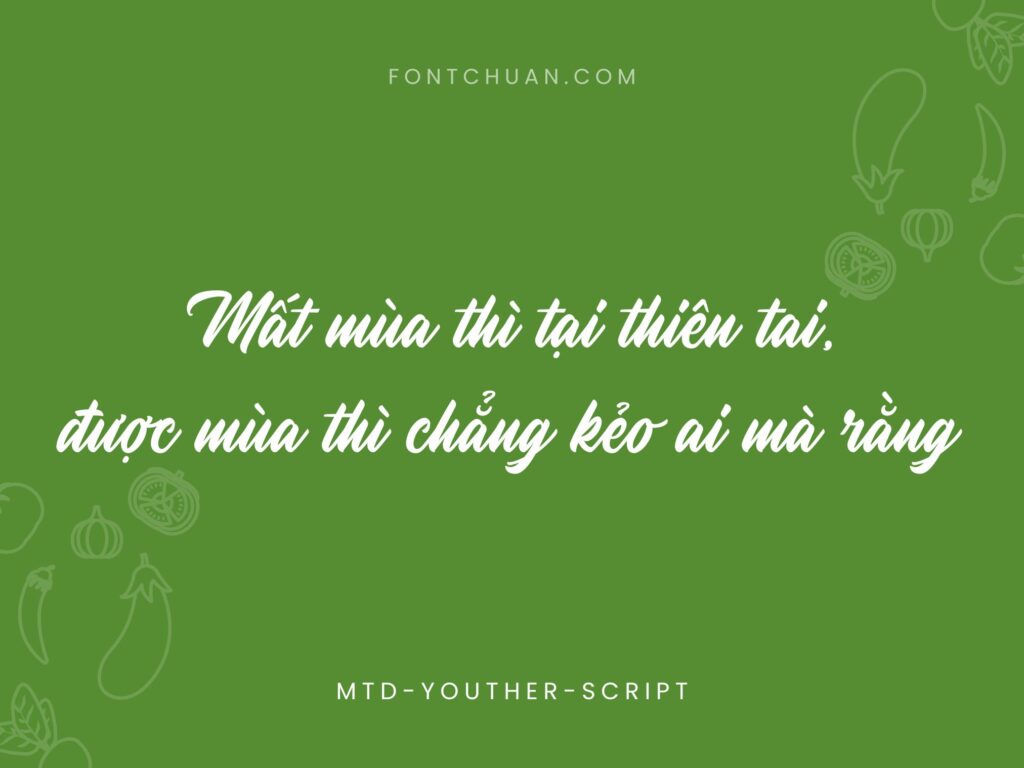
Font MTD Youther Script Việt Hóa
Font MTD Youther Script là một kiểu chữ viết tay phong cách tự nhiên, được thiết kế bởi Letterhend Studio và đã được Việt hóa bởi Mộc Hạ. Font này hỗ trợ đầy đủ tiếng Việt cùng hơn 90 ngôn ngữ khác, giúp tăng cường khả năng sử dụng cho nhiều dự án thiết kế đa dạng. Đây là một trong những font được cộng đồng thiết kế đánh giá cao bởi sự linh hoạt và hiện đại, đồng thời mang lại cảm xúc cá nhân hóa rõ nét trong từng sản phẩm.
MTD Youther Script nổi bật với các đường nét phóng khoáng, đều đặn và mang hơi hướng năng động, rất phù hợp cho những thiết kế cần thể hiện tính sáng tạo và cá tính riêng. Font đặc biệt lý tưởng cho các dự án về nhận diện thương hiệu, thiết kế bao bì, tiêu đề tạp chí, poster, và thiệp mời. Với phong cách đầy cảm hứng và tinh tế, font này phù hợp cho các ngành nghề như quảng cáo, giáo dục, công nghệ, thiệp cưới và ảnh cưới. Ngoài ra, nó cũng là lựa chọn tuyệt vời cho các dịp như Tết, Giáng sinh, Valentine và nhiều sự kiện lễ hội khác.